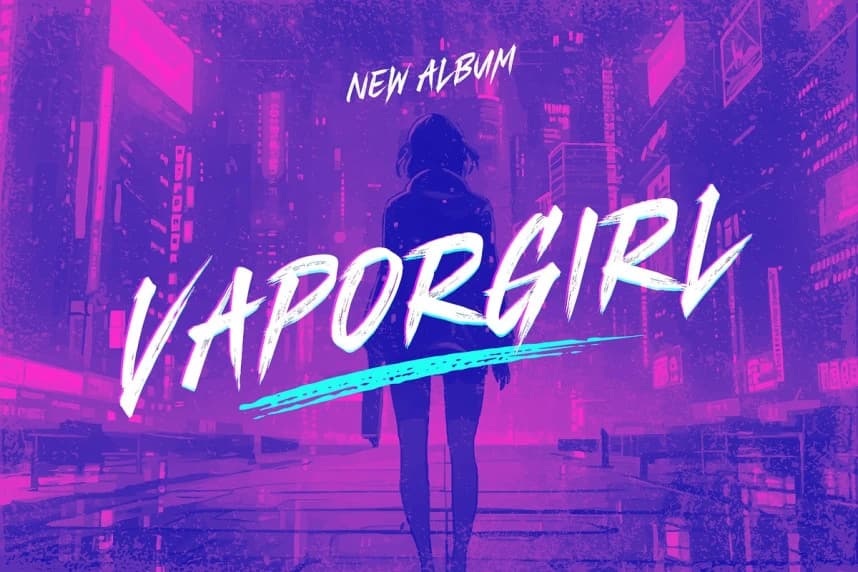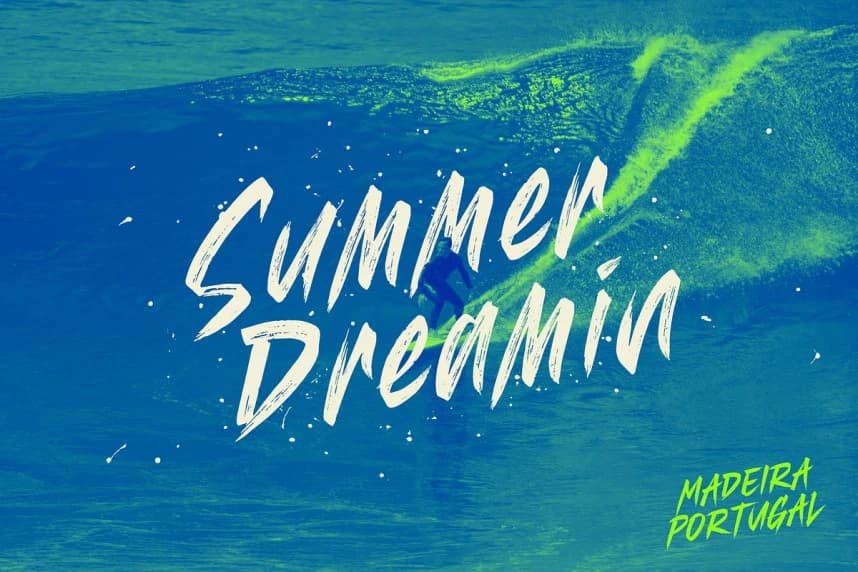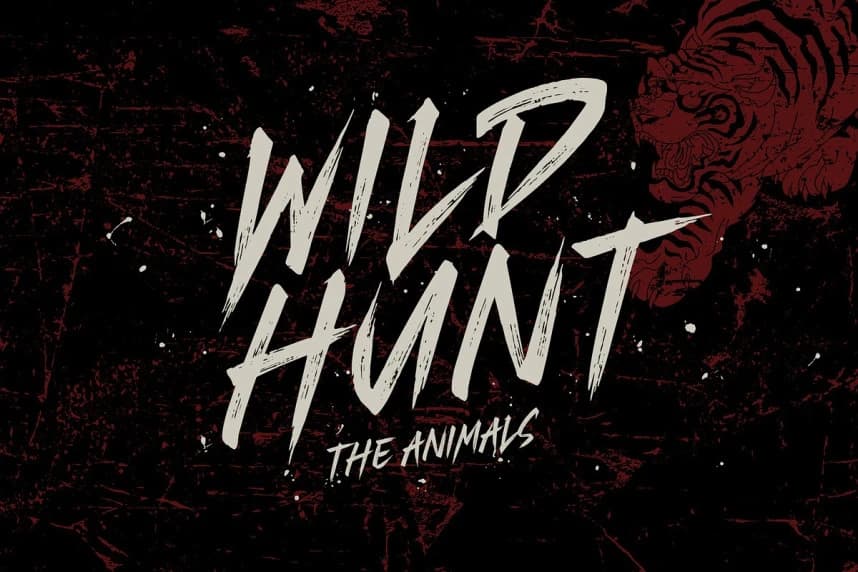
Gakuran Brush Font
Gakuran Brush Font, hızlı ve dokulu fırça darbeleriyle el çizimi yazıların ham enerjisini yakalayan cesur, düz fırça stilinde bir gösteri yazı tipidir. Göz alıcı başlıklar ve öne çıkan metinler için idealdir.
Gakuran Brush Font, hızlı, dokulu vuruşlar içeren düz fırça stilinde cesur bir gösterim yazı tipidir ve el çizimi harflerin ham enerjisini yakalar. Göz alıcı başlıklar ve öne çıkan başlıklar için mükemmeldir.
Gakuran Brush